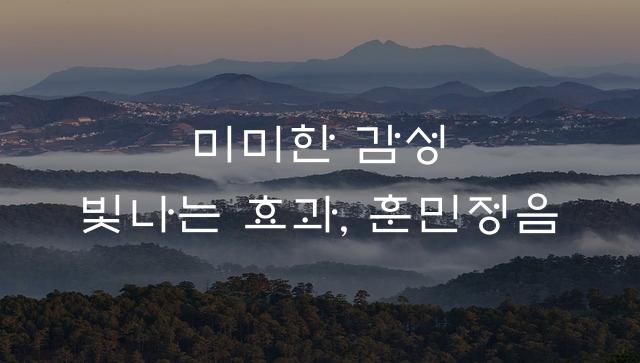
EBS훈민정음새론체는 꽉 찬 고딕 스타일의 현대적 디자인과 옛날 한글의 전통적 느낌을 결합한 폰트입니다. 이 폰트는 전통과 현대의 조화를 통해 감성적이고 따뜻한 분위기를 자아냅니다.
EBS훈민정음새론체은(는)
기본 고딕, 명조/전통, 레트로, 굵은 고딕, 복고풍, 단단함 계열의 생김새를 가지고 있으며
교육 자료, 보고서/문서 등에서 자주 활용되며, 효과적인 메시지 전달에 적합합니다.
이 폰트는 교육, 출판/미디어 분야에 잘 어울리며,
명확한, 전문적인 느낌을 담고 있는 것이 특징입니다.